Type Trends : 2022 Q3 Trends par Ryan Arruda et Jason Ramirez
Nous avons contacté deux designers pour ce numéro de Type Trends - et nous avons rapidement découvert que même s'ils avaient des contrats apparemment très différents, ils travaillaient tous les deux avec des objectifs de conception étonnamment similaires. Nous avons posé beaucoup de questions et en avons tiré de précieux conseils en matière de typographie.
Deux formidables créateurs de tendances
Ryan Arruda crée des emballages à tomber par terre et un design promotionnel pour Tree House Brewing Company, dans le centre du Massachusetts. Il est également concepteur indépendant et utilise les caractères et la typographie comme principaux outils de son répertoire de conception aux multiples facettes. Un emploi précédent dans le domaine de la conception, du contenu et de polices à MyFonts et Monotype l'a aidé à perfectionner son art.
Jason Ramirez est directeur artistique et concepteur primé pour Viking/Penguin Books, à New York. Il a été récompensé par l'AIGA Eye on Design, le concours AIGA 50 Books | 50 Covers, le Type Directors Club, le New York Book Show et les magazines Communication Arts et Print. En outre, ses projets ont été publiés dans plusieurs ouvrages relatifs à la conception graphique et à l'édition. Il a également été invité à donner des conférences à la Parsons School of Design et au NYU Center for Publishing.
Points de vue partagés
Quel est le point commun entre ces créateurs apparemment divergents ? Ils créent tous deux un design de point de vente qui se limite généralement à un ou deux choix de polices de caractères. Cela nécessite un choix réfléchi de police et une association astucieuse. Ils partagent également l'objectif commun de créer un design typographique sans prétention, mais qui attire l'attention. En outre, ni Arruda ni Ramirez ne se satisfont du statu quo typographique.
Ils sont tous deux conscients de la valeur de la nostalgie inspirée par la typographie pour faire passer un message. Tous deux n'hésitent pas à prendre des risques typographiques, mais les tempèrent par des choix réfléchis. Ils sont convaincus que les caractères peuvent avoir une personnalité ou, du moins, être remarquablement expressifs. Tous deux se plongent également dans les racines et les nuances de chaque projet, avant d'en concevoir le design.
Le pouvoir de la nostalgie
"Tout ce qui est ancien est à nouveau nouveau", déclare Arruda, "avec une voix actualisée, un raffinement supplémentaire et de nouveaux artisans à la barre. Je pense que le processus de retour à l'esthétique d'antan s'est accéléré, car les outils de conception ont continué à se démocratiser. Les caractères bien conçus ne sont plus l'apanage des dessinateurs de caractères permanents.
"Si les cinq dernières années ont été marquées par le retour en force des styles des années 1970, les années 1980 et 1990 sont elles-mêmes en pleine effervescence", poursuit-il. "Bien sûr, il y a une forte dose de nostalgie et d'ironie dans le mélange, mais je pense que nous constatons également une appréciation pour des formes de lettres magnifiquement travaillées qui sont peut-être tombées en désuétude uniquement parce que l'esprit esthétique a changé - et non pas parce que les conceptions étaient médiocres.
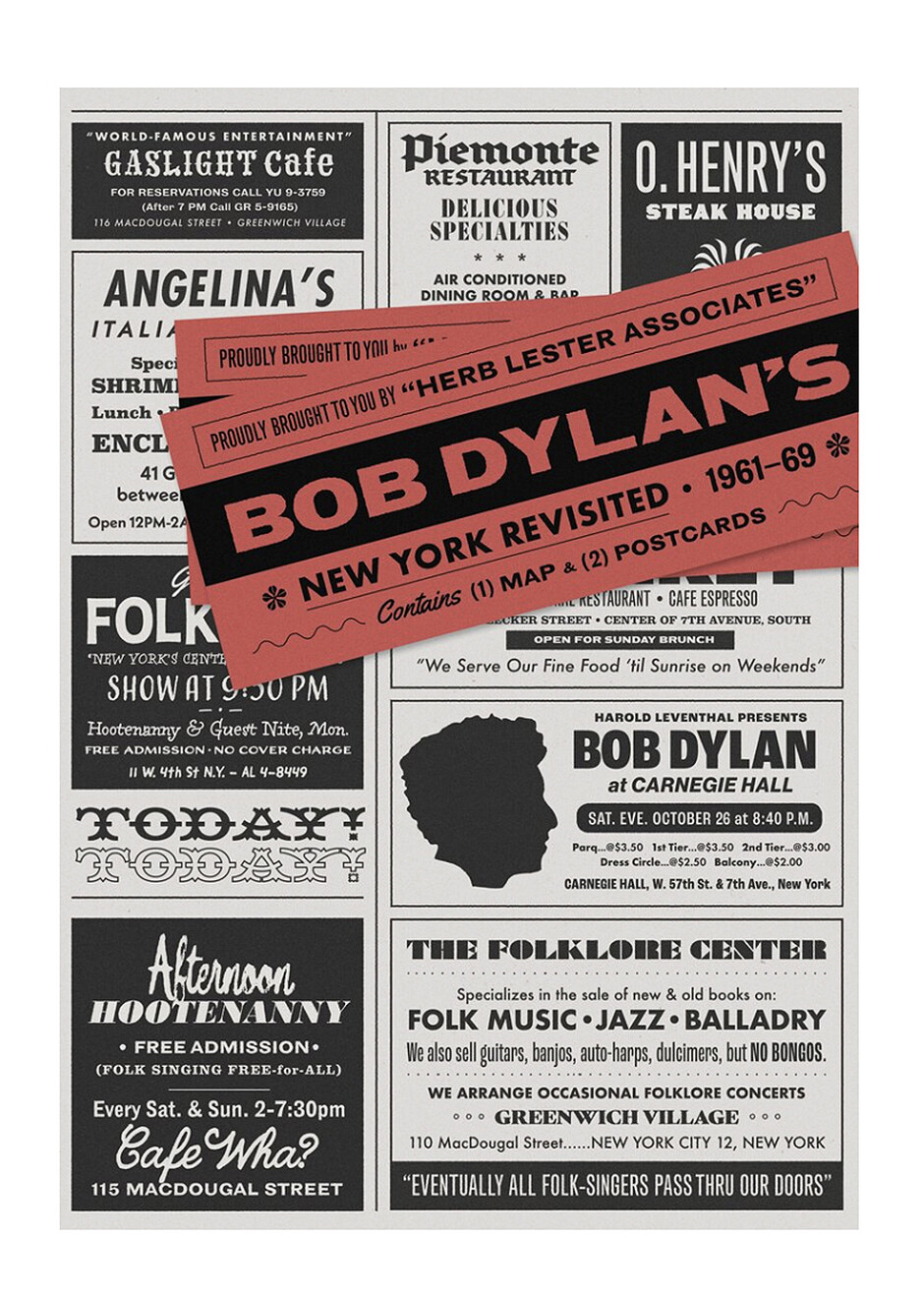
Ramirez, se fait l'écho de cette appréciation. "Un style de typographie plus nostalgique, qui reprend les classiques de la typographie popularisés dans les années 1960 et 1970, est manifestement bien accueilli. Ces formes typographiques anciennes sont conviviales, familières et peut-être même ludiques. Elles regorgent d'empattements souples, de courbes douces et de traits angulaires largement évasés."
"L'adoration pour cette esthétique vintage se traduit par l'utilisation de polices de caractères classiques de l'époque, ou de leurs cousines réimaginées (parfois sous forme de dessins sur mesure), pour de nombreux projets de rebranding. Si les polices de caractères nostalgiques peuvent sembler à certains une nouveauté par rapport à la typographie moderne, ces formes de lettres offrent une promesse d'authenticité. Cette esthétique vintage - classique ou réimaginée - peut également insuffler aux marques un sentiment d'héritage, créant ainsi une plus grande légitimité sur un marché de plus en plus concurrentiel."
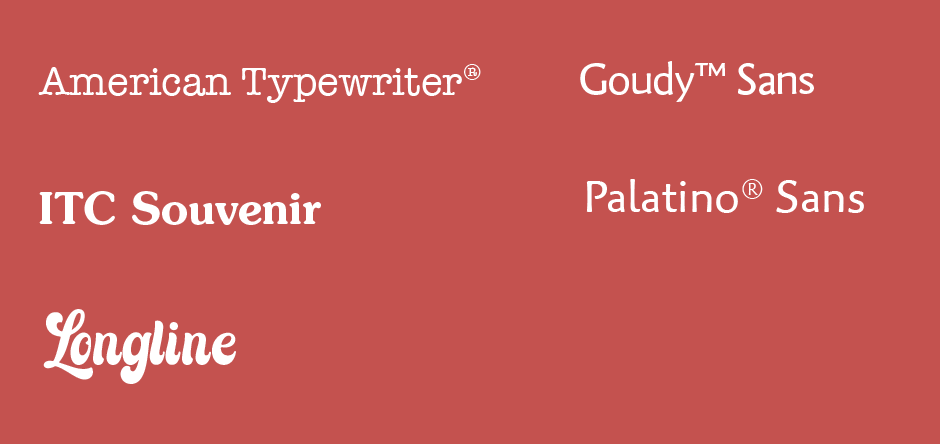
Fade ou courageux
Je ne suis pas sûr d'adhérer à l'approche de la "coupe de cristal"", déclare M. Arruda. "Bien sûr, il arrive que les concepteurs soient obligés d'utiliser certaines polices de caractères, mais les choix typographiques ajoutent absolument de la saveur à la composition qu'un concepteur crée - et il n'y a rien de mal à le faire. La solution n'est pas de s'en tenir à la recherche de l'exceptionnellement fade, par crainte d'être distrait.
"J'ai un faible pour les affiches éphémères du milieu du XIXe siècle", poursuit Mme Arruda. "Pensez-y : de grandes affiches typographiques avec de grandes lettres et des assortiments denses d'informations. Il y a quelque chose dans la collision des tailles, des styles et des largeurs de caractères qui donne à ces artefacts un charme unique".
Si plus de deux ou trois polices de caractères sur la couverture d'un livre peuvent donner lieu à une composition chargée, confuse et peu esthétique", explique Ramirez, "chaque livre est unique, avec son propre ensemble de circonstances, et mérite un traitement de couverture tout aussi distinct". Les différentes polices de caractères utilisées sur la couverture de Frankenstein à Bagdad faisaient partie intégrante du concept de design.
"Le livre est une relecture contemporaine du mythe de Frankenstein qui se déroule dans la ville de Bagdad occupée par les États-Unis, où un charognard local ramasse des morceaux de corps humains disparates dans les rues déchirées par la guerre et les assemble pour créer un monstre improbable qui laisse une traînée de mort dans son sillage. Un photographe/reporter d'un hebdomadaire d'information finit par rencontrer et interviewer le monstre, pour découvrir sa surprenante humanité.
"J'ai créé de fausses coupures de presse comme principal véhicule pour réinterpréter et réimaginer le monstre comme la somme de ses parties humaines et de ses paroles prononcées lors de l'interview du journaliste.
Personnalité typographique
Chaque police de caractères a une personnalité", explique M. Ramirez. "Chaque caractère a quelque chose à dire. Et dans la conception d'une couverture de livre, une police de caractères peut faire une promesse implicite au lecteur. C'est ce principe directeur qui guide ma façon de travailler avec les caractères".
La jaquette du livre "The Twelve Lives of Alfred Hitchcock" en est un parfait exemple. Le livre est présenté par l'éditeur comme une "interprétation nouvelle et innovante de la vie, de l'œuvre et de l'influence durable du cinéaste le plus emblématique du vingtième siècle".
"Le poids et la lourdeur des caractères sans empattement compressés confèrent une gravité qui témoigne de l'ampleur de ce portrait nuancé et étendu d'Hitchcock, ainsi que de l'influence phénoménale et de l'héritage de cette icône culturelle. Les caractéristiques exagérées et excentriques de ces formes de lettres semi-brillantes confèrent à cette biographie un ton à la fois autoritaire et chaleureux. En variant la hiérarchie, l'échelle et l'emplacement, la typographie percutante encadre le sujet d'une manière qui permet de se concentrer sur le portrait provocateur d'Hitchcock".
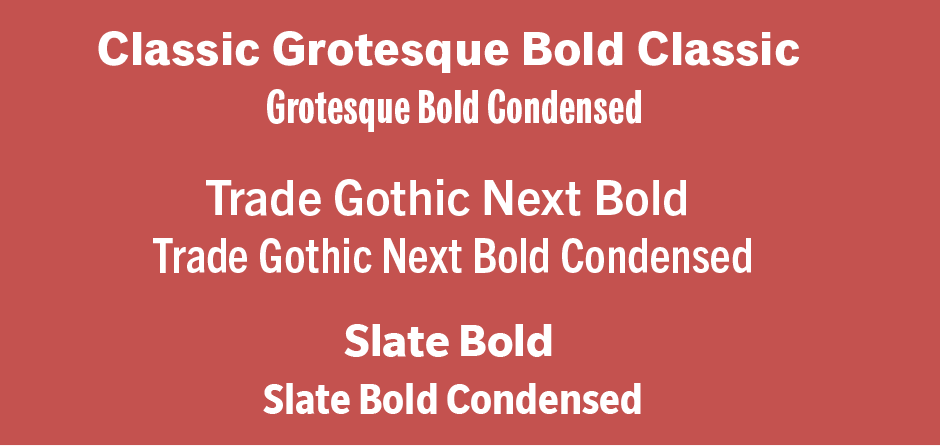
"Tree House est un endroit merveilleux où l'on peut prendre des risques", déclare Arruda, "et c'est Nate Lanier, le PDG de Tree House, qui est à l'origine de cette initiative. Bien que nous utilisions régulièrement des traitements typographiques standardisés, ils ne sont jamais absolus ; s'il y a une bonne raison de rompre avec une convention, nous l'encourageons vivement.
"L'équipe s'est par exemple attelée à un projet pour la sortie annuelle de la Wish List de Tree House : un trio hivernal de bières d'accompagnement, d'infusions froides et de cafés torréfiés.
"Nous souhaitions canaliser la riche chaleur des emballages de vacances d'antan, tout en veillant à ce que les trois produits, bien que complètement différents, restent cohérents en tant que groupe. Outre les tons festifs de rouge, de vert et de crème, la palette typographique utilise un script calligraphique expressif, un sans empattement imprimé à la main, un design glyphique "Copperplate-esque" et une lettre noire festive. Ce qui aurait pu être une cacophonie hétéroclite de polices de caractères a été tempéré par l'utilisation modérée de chacune d'entre elles, sachant qu'elles apportaient un contraste à la conception - sans la dominer."
Arruda et Ramirez nous ont fourni des lignes directrices avisées, plutôt que des tendances éphémères. Ils nous montrent la voie vers une conception typographique puissante, expressive et, en fin de compte, réussie. Ce ne sont peut-être pas des tendances, mais ce sont des lignes directrices intelligentes à suivre.